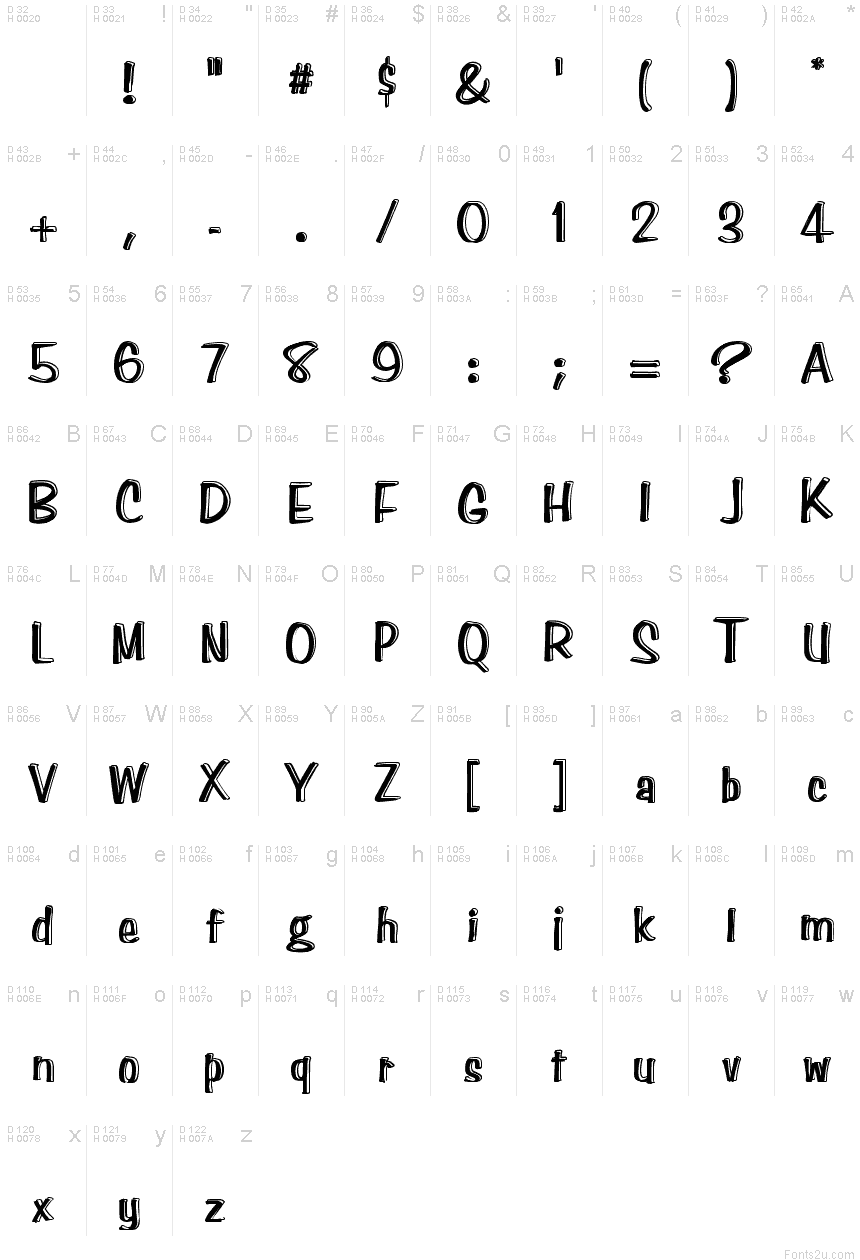
Paghetti è un font display gratuito disegnato a mano da STAR Retrieval Systems, basato su Stimpson; ha un sapore Art Nouveau rilassato con lettere che sembrano colate piuttosto che costruite. I tratti oscillano e si gonfiano in morbidi cappi, con un bordo delineato a inchiostro che conferisce al font un ritmo leggermente stravagante, quasi come quello di alcuni spaghetti.
Si adatta perfettamente a poster, menu di bar, packaging alimentare, copertine di fanzine e branding giocoso dove un titolo richiede più movimento che perfezione. Essendo un font gratuito, funziona al meglio in titoli brevi, linee di copertina e scritte in stile logo, poiché le sue curve elastiche e le giunture irregolari conferiscono anche a poche lettere una presenza colloquiale e fatta a mano.